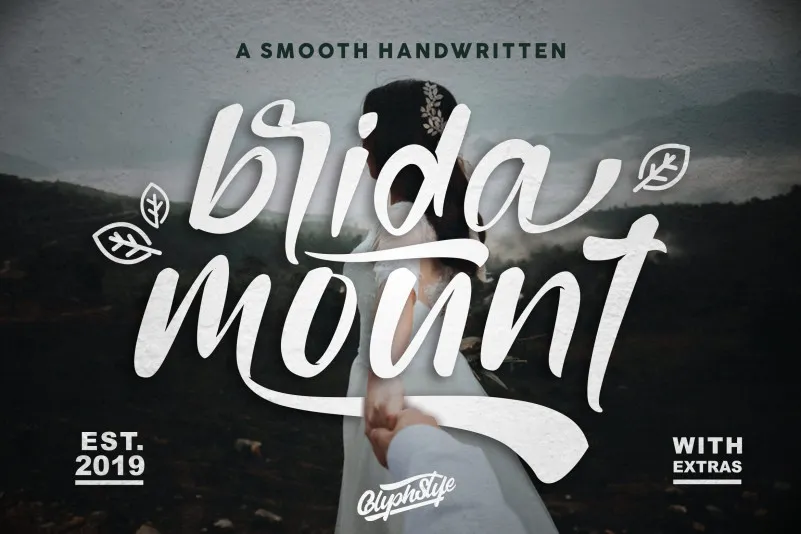
Bridamount Script Font – Fonte Grátis
Bridamount Script Font
Bridamount Script Font é uma fonte de escrita manuscrita suave e detalhadamente curvada, perfeita para projetos com tema aventura. Suavemente fluida e detalhadamente elaborada, esta fonte foi criada pelo Designer GlyphStyle para quem busca um toque de elegância na escrita digital. Seja para criações de marca ou logotipos, decoração para casamentos, postagens nas redes sociais, anúncios, cartões de visita, produtos de moda, citações, capas de revistas, etiquetas, fotografias, marcas, convites e materiais de embalagem, Bridamount Script Font certamente encaixa-se perfeitamente. Ela adicionará um toque suave e elegante a qualquer projeto que precise da sensação única de escrita manuscrita. Experimente Bridamount Script Font para dar aos seus projetos aquela pitada especial de personalidade e charme.